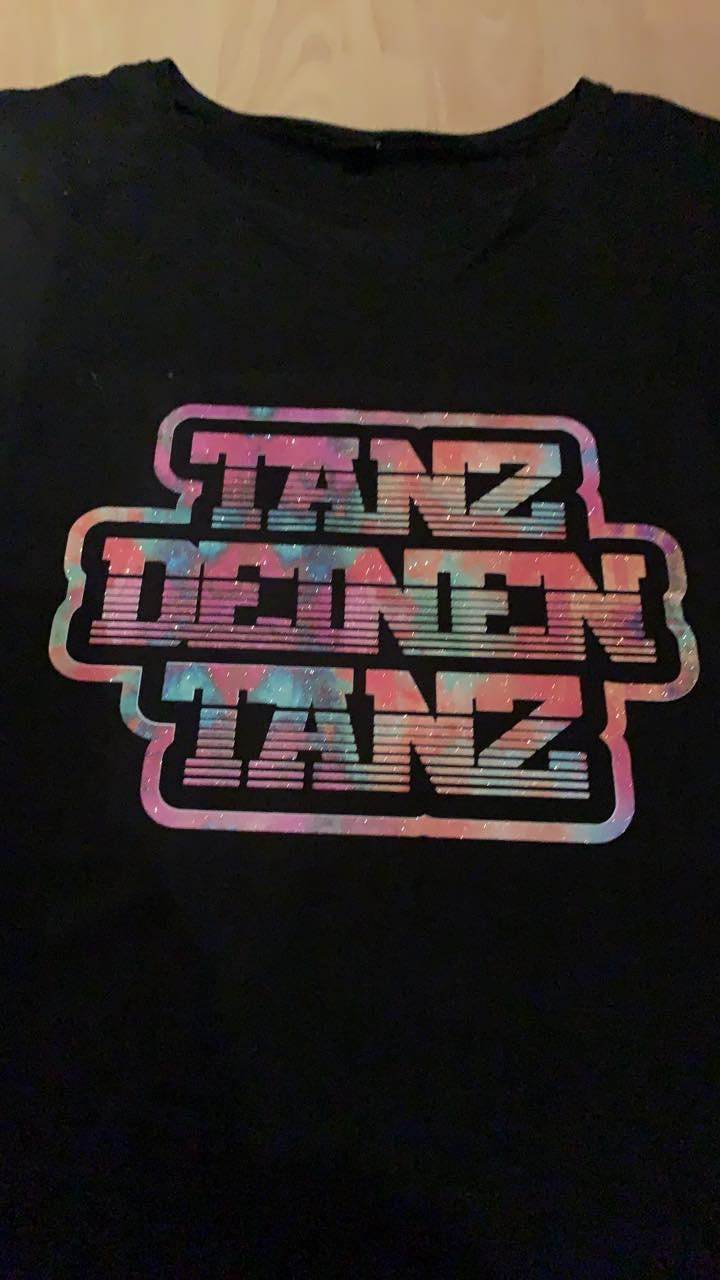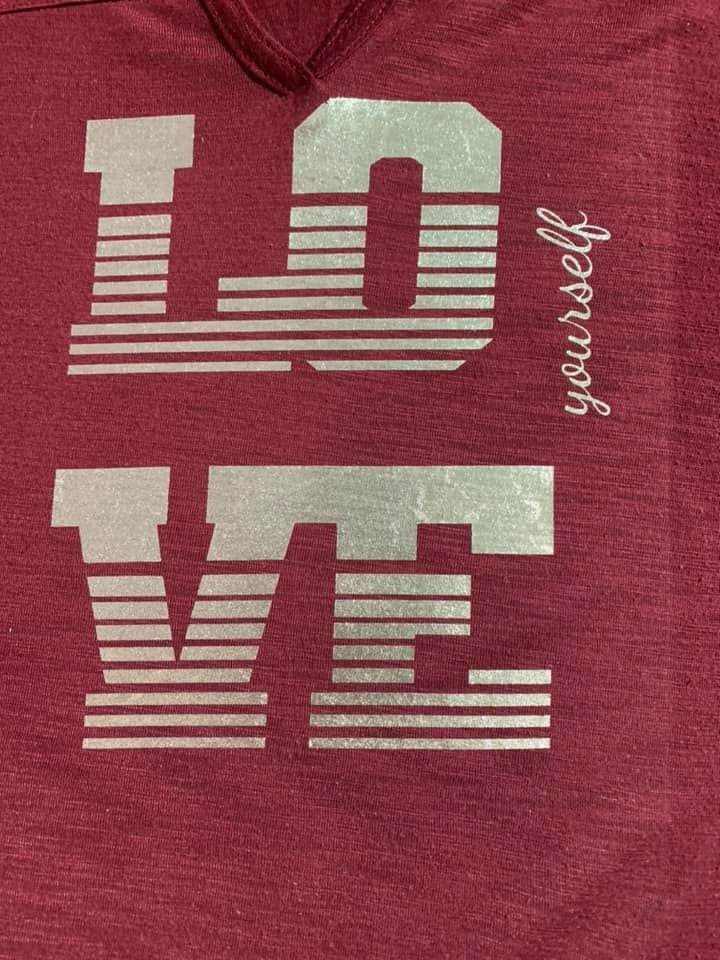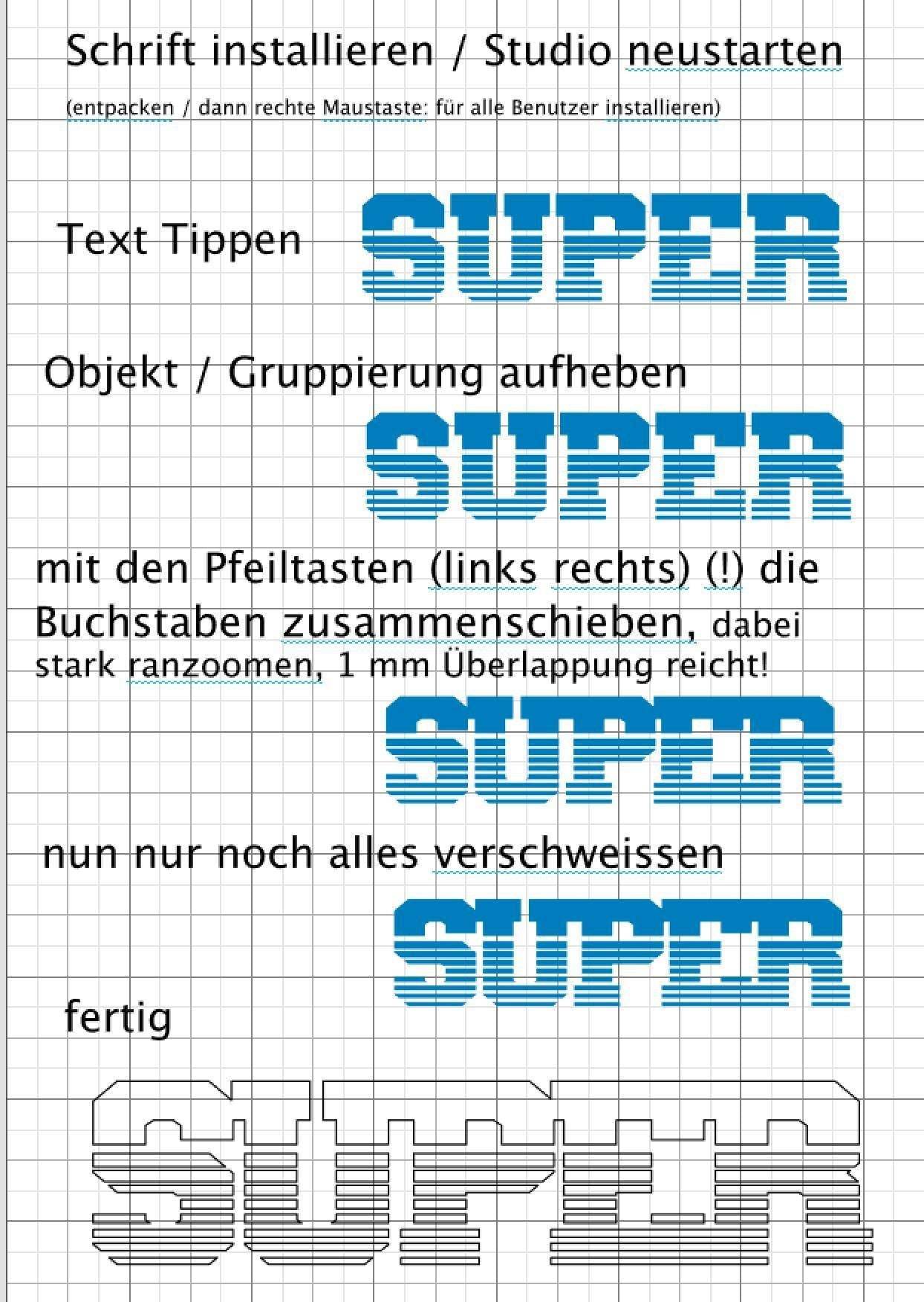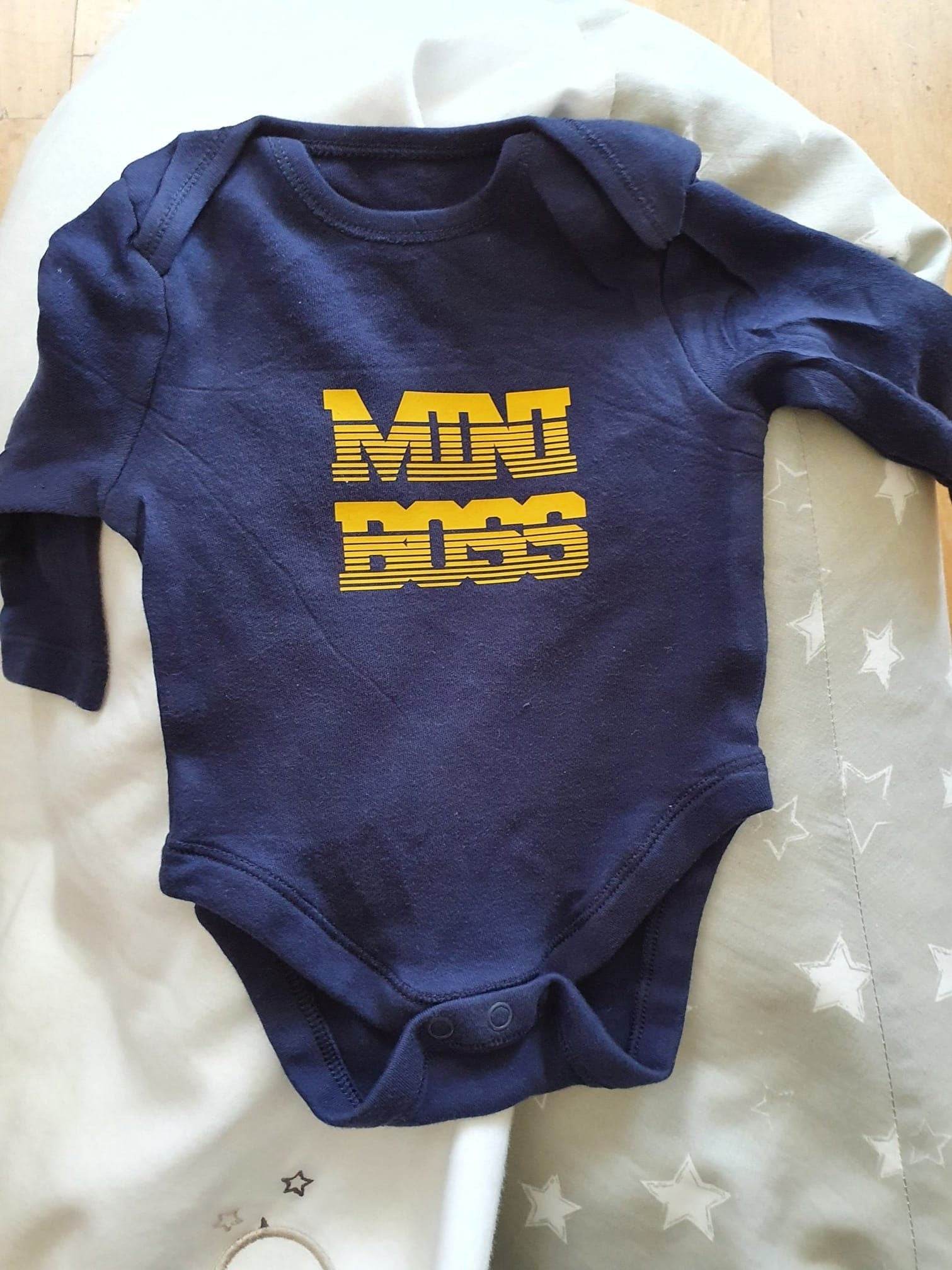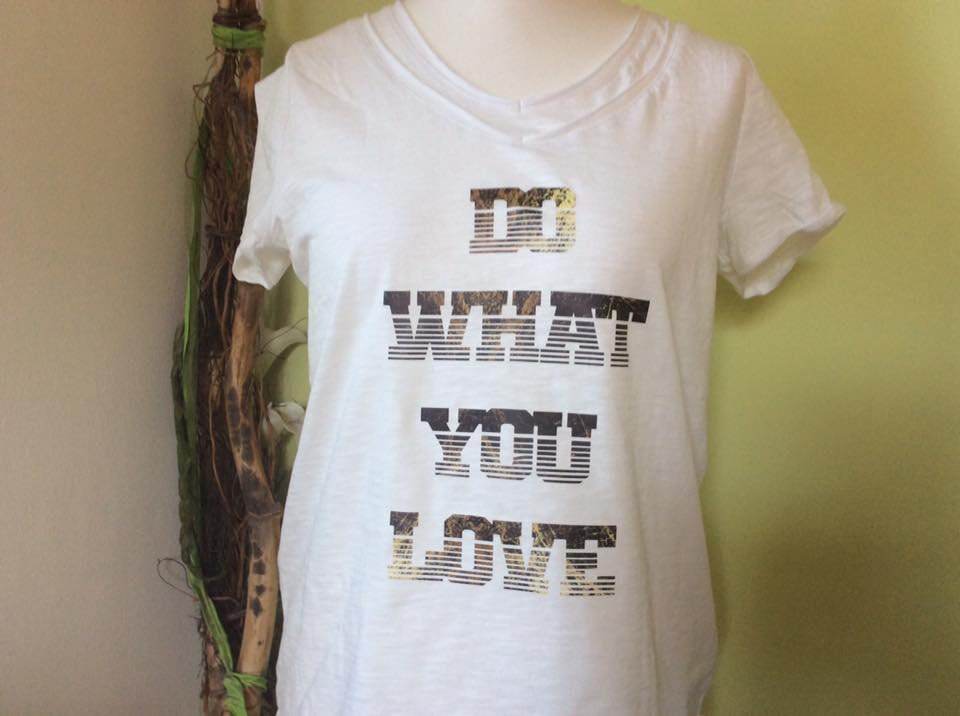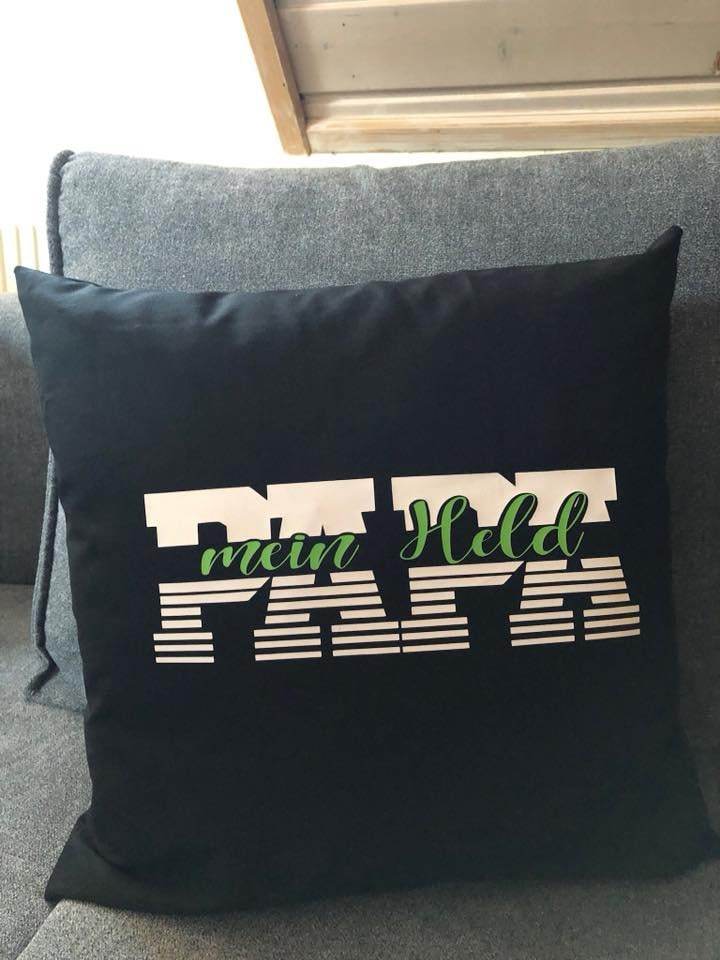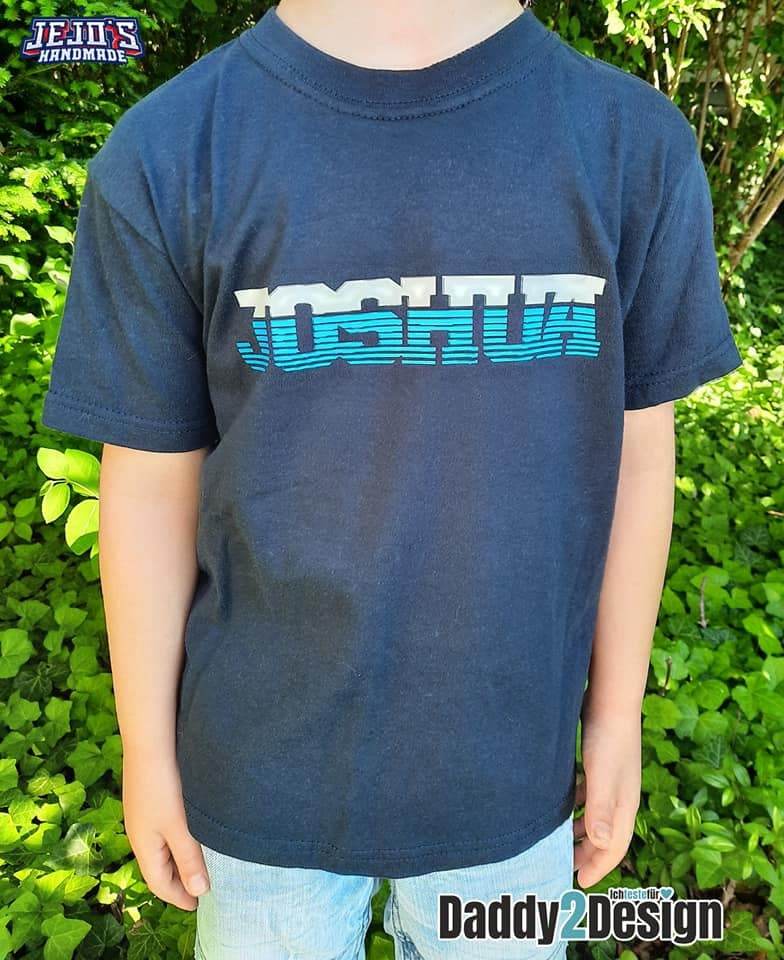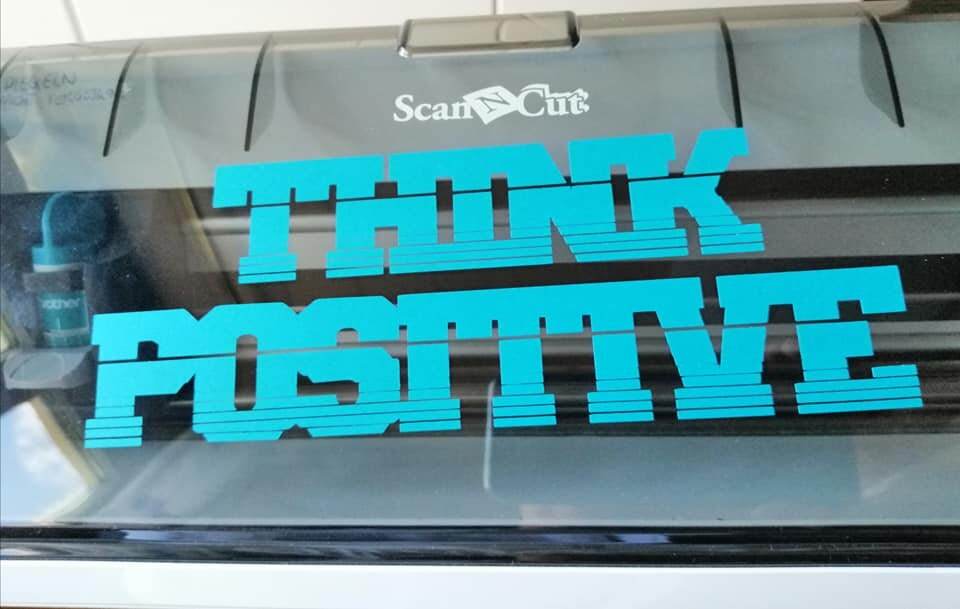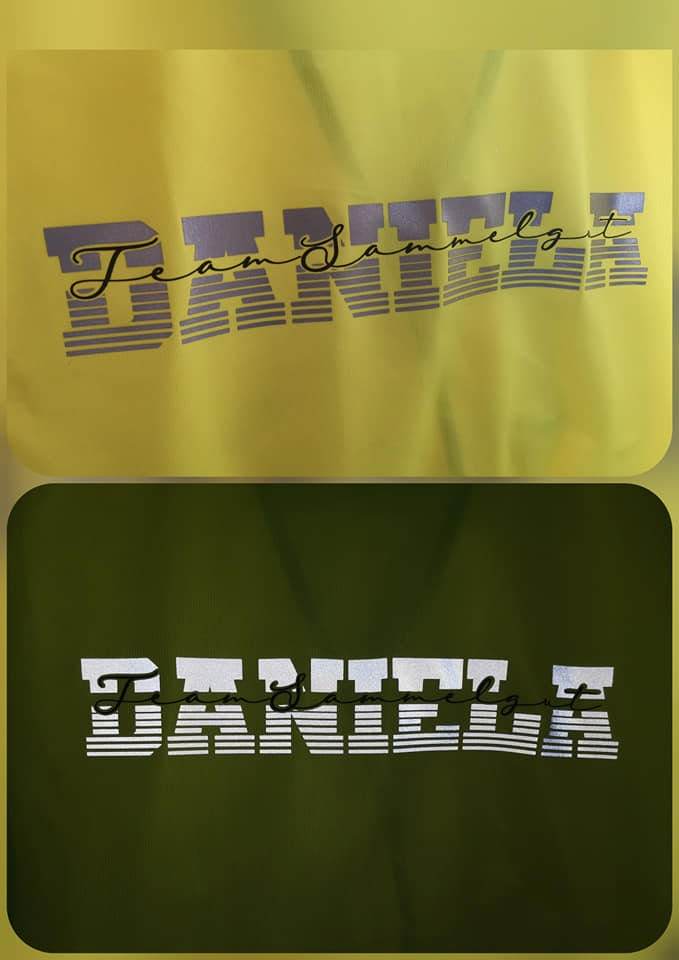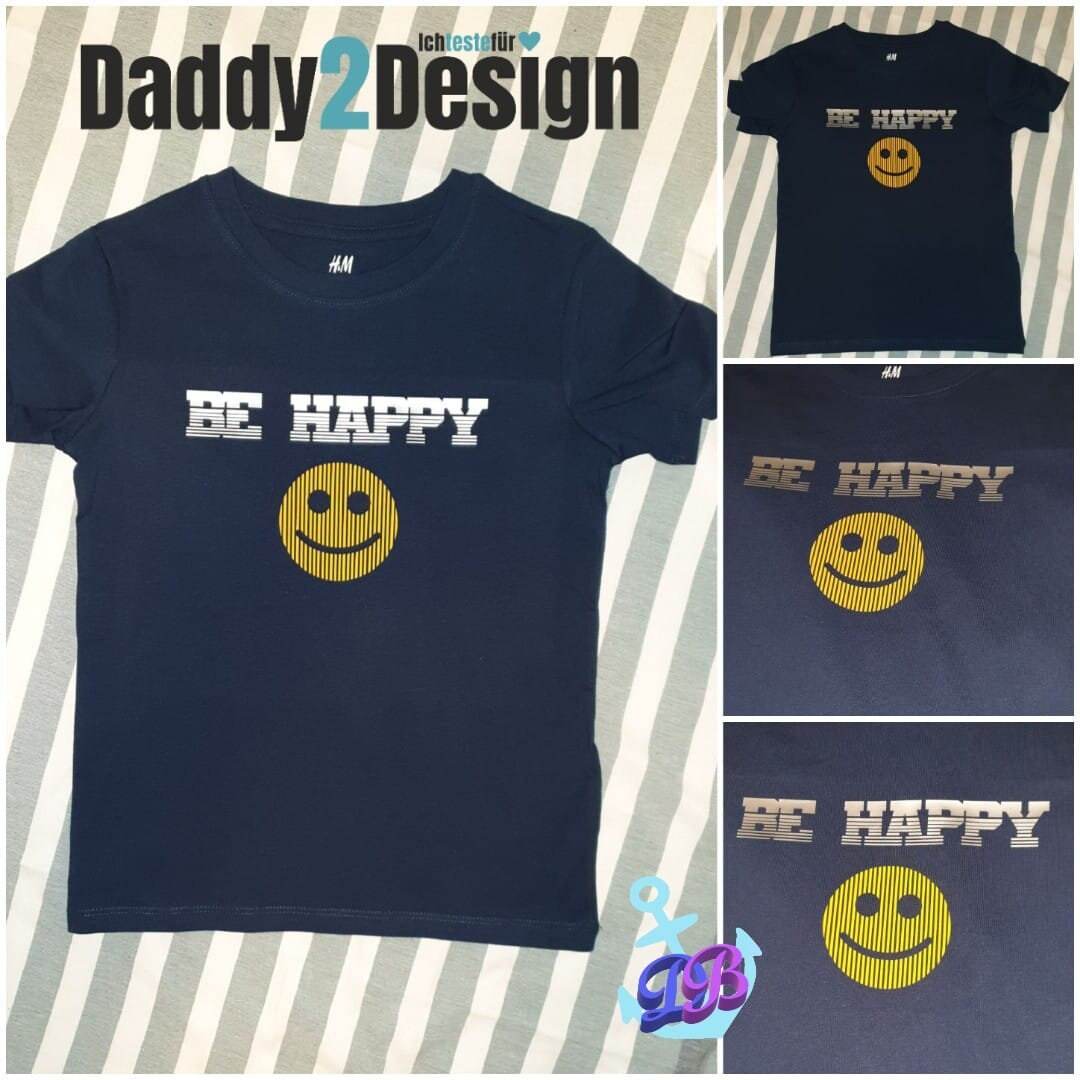
Wir haben ein ganz spezielles PLOTT ABC als ECHTE SCHRIFTART gestaltet,
in dem sich nicht nur ein cooler Effekt tippen lässt,
nein man kann durch einfaches Zusammenschieben einen EINZIGARTIGEN Kombinations-Effekt ganz ganz ganz leicht selbst erstellen.
WIE einfach es funktioniert seht ihr im Bild 3 <3 <3 <3
Aber das ist nicht mal Alles, man kann auch noch einen supercoolen DOPPELEFFEKT ganz leicht erstellen. <3 <3 <3
Es sind NICHT alle Zeichen verfügbar und nur Grossbuchstaben Zahlen und Zeichen Enthalten: A-Z und 0-9 dazu ? . : !